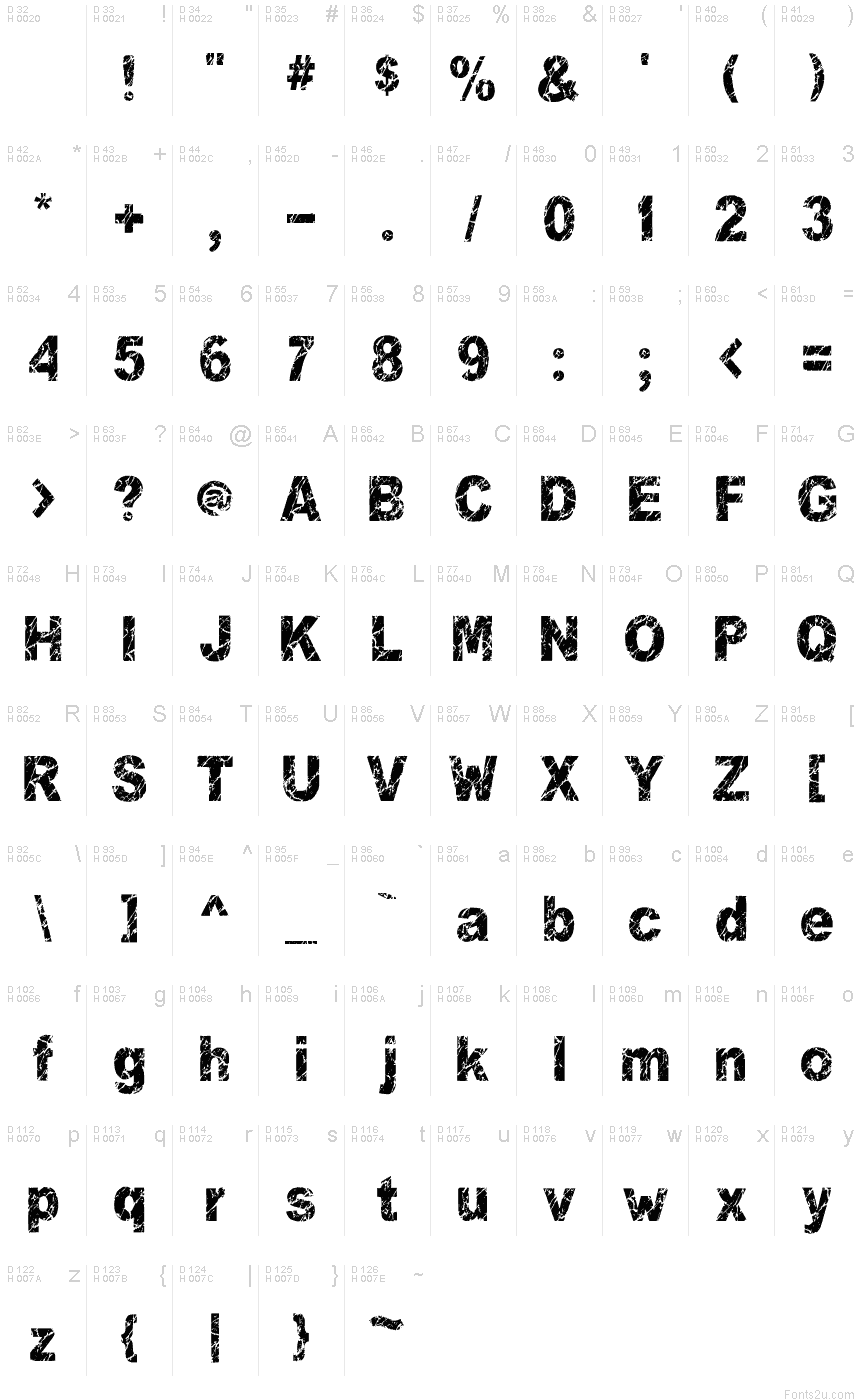
You Rook Marbelous
You Rook Marbelous autorstwa R. Gasta z GreyWolf WebWorks to darmowy, erodowany font typu display o surowej, marmurkowej teksturze, która wygląda, jakby została wykuta w malowanym kamieniu. Litery są duże i masywne, ale ich popękana powierzchnia nadaje im niespokojny charakter, z pęknięciami i ubytkami powtarzającymi się w całym kroju pisma, dzięki czemu nie sprawiają wrażenia jednorazowego efektu.
Świetnie pasuje do plakatów, okładek albumów, horrorowych ulotek, tytułów gier i surowych okładek zinów, gdzie to właśnie ta „zużyta” tekstura buduje cały klimat. Jako darmowy font, doskonale sprawdza się też w krótkich nagłówkach, logotypach i wstawkach, które potrzebują tego obdrapanego, naznaczonego zębem czasu wyglądu, bez konieczności stosowania dodatkowej obróbki graficznej.